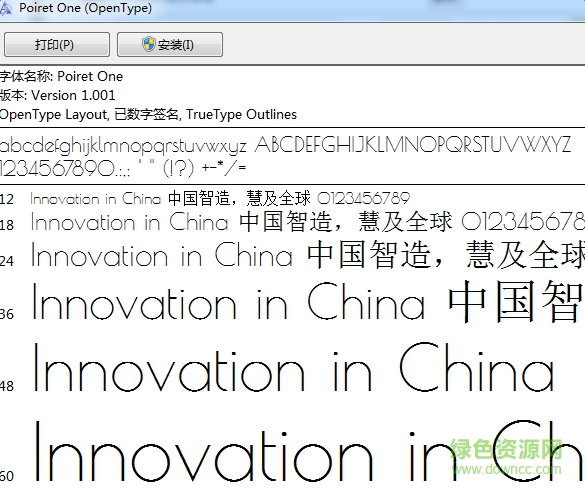
POIRET字體是一款超好用的英文個(gè)性字體,該字體簡單大氣,能夠使用于多種場合,絕對(duì)是廣大用戶必不可少的一款字體,需要的用戶就趕快來綠色資源網(wǎng)免費(fèi)下載收藏吧!
POIRET字體是一款極具個(gè)性的字體,該字體十分飄逸,彰顯了自己的個(gè)性,有喜歡的朋友可以來綠色資源網(wǎng)下載使用!